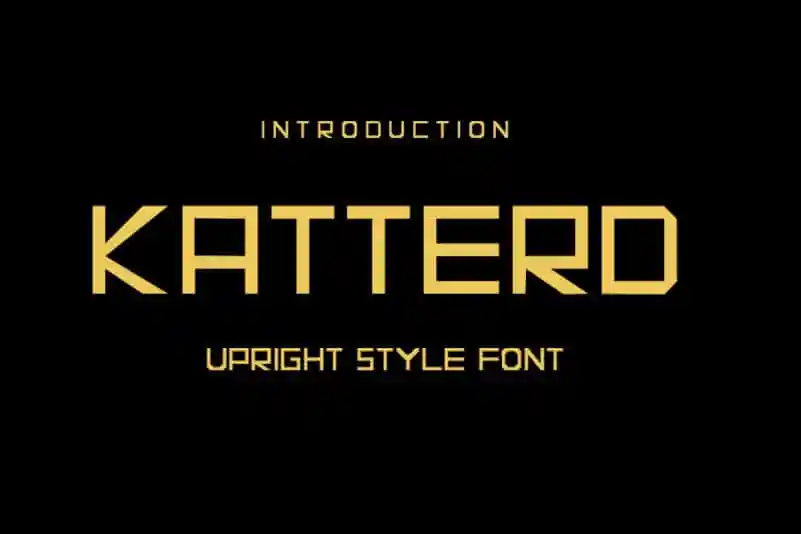
KATTERD Display Font é uma elegante tipografia sem serif que mantém influências clássicas do grego enquanto se atualiza e permanece fresca. Esta versatilidade atraí criatividades de diversos campos, desde enfeites de letras até títulos de mídia, passando por materiais de papelaria. Perfeito para quem procura um equilíbrio entre clássico e contemporâneo, KATTERD Display é uma opção ideal para projetos que valorizam criatividade e elegância moderna. Engane-se com o inermediaSTUDIO, fornecedor desta fonte sem-serif, que se destaca na criação de tipos de letras atemporais e vibrantes.